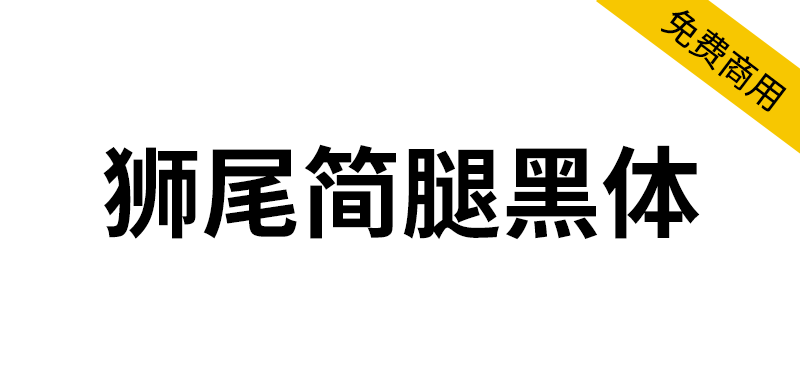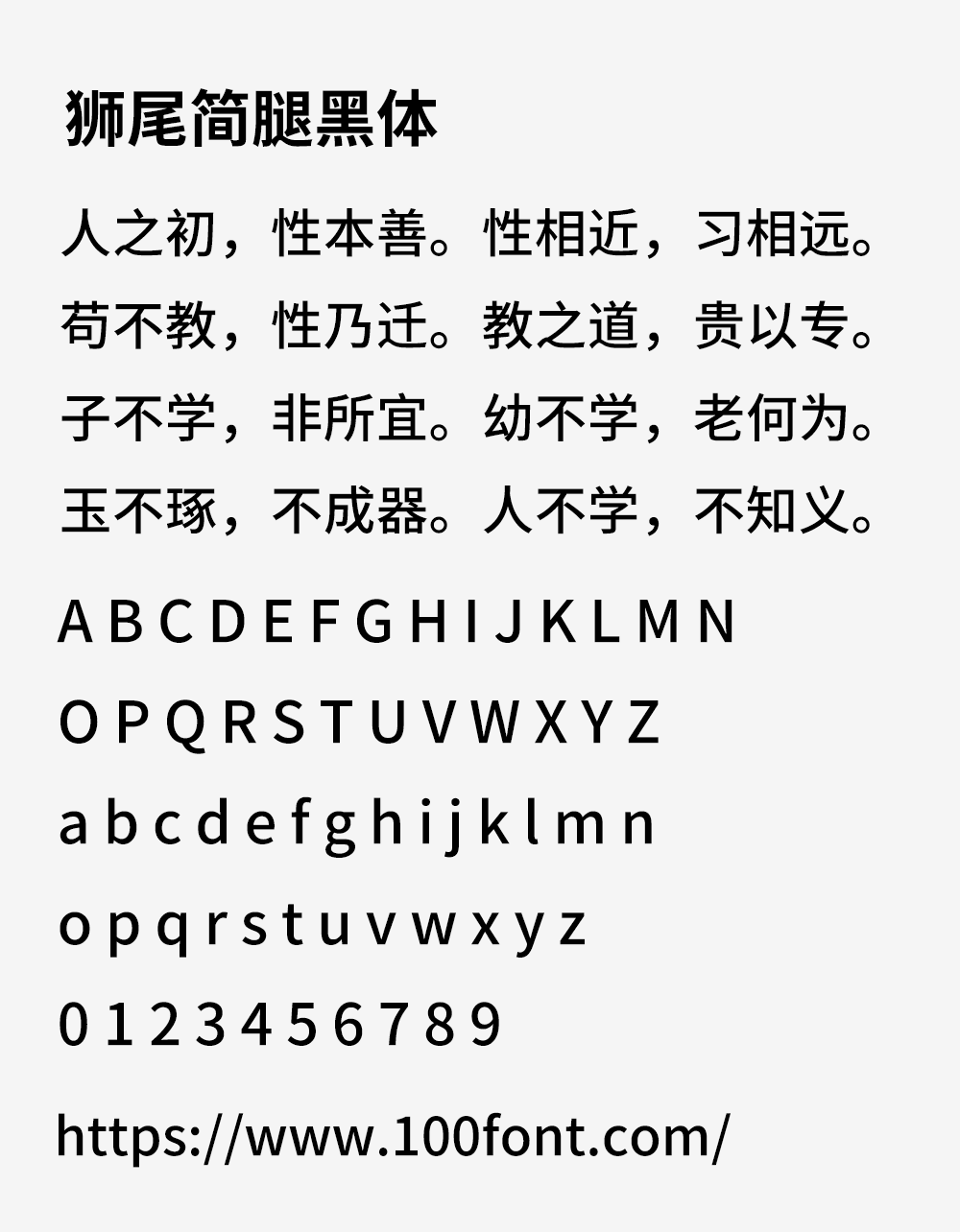
狮尾简腿黑体基于思源黑体的繁转简字型(繁转简的意思就是输入繁体字时,会自动显示成简体字),狮尾简腿黑体的特色是「繁体字转成简体字的字型档」,由于是转成简体,所以能处理「一简对多繁」。狮尾简腿黑体设计上针对笔画粗细有7种字重,所以不论大标、小标、简单的段落排版都能清晰辨识。可以免费商用,欢迎大家自由应用、自由优化、自由改作!
狮尾简腿黑体与「狮尾简中黑体」差别在有没有「拔脚」,「拔脚」就是会有较少的笔画,例如移除「口」字的左右下角会多出的短线条。有拔脚的字会较圆,但是会造成有些字因直接去掉腿后左右不平衡、左右不对衬的「悬空」问题。改使用「腿」系列字体就不会有这个问题。